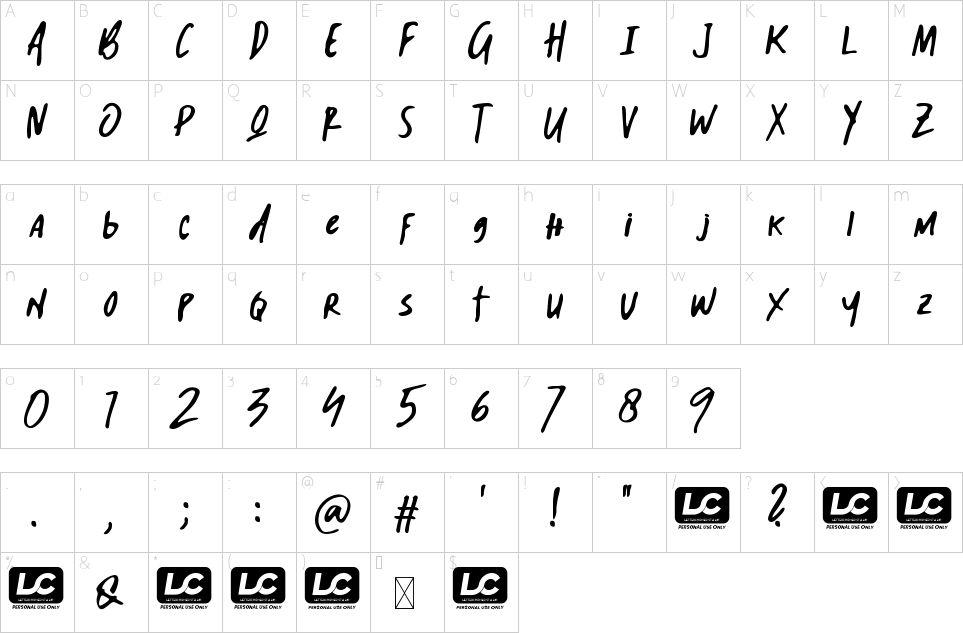
Austria Ink Font – Download Grátis
Descubra Austria Ink, uma fonte elegante para seus projetos gráficos digitais. Desenvolvida pela Lettercorner Studio, esta fonte vem em versões para Windows e Mac. Com uma aparência minimalista e sofisticada, Austria Ink é perfeita para criações que exigem um toque de minimalismo no design. Se você está procurando por uma fonte que combine elegância com simplicidade, Austria Ink é uma escolha excelente. Com apenas 269 downloads, esta fonte provavelmente é o item de design que você não queria perder. Instale-a em seu próximo projeto e encontre o equilíbrio entre modernidade e refinamento. Seja em um ambiente de trabalho ou um projeto de design pessoal, Austria Ink é uma fonte que certamente enriquecerá seu design.